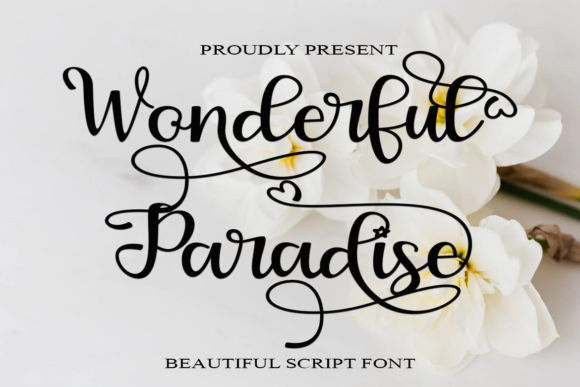
Wonderful Paradise - это уникальный и элегантный рукописный шрифт.
Он выглядит красиво на различных дизайнах, требующих персонализированного стиля, таких как свадебные приглашения, благодарственные открытки, свадьбы, поздравительные открытки, логотипы и так далее.